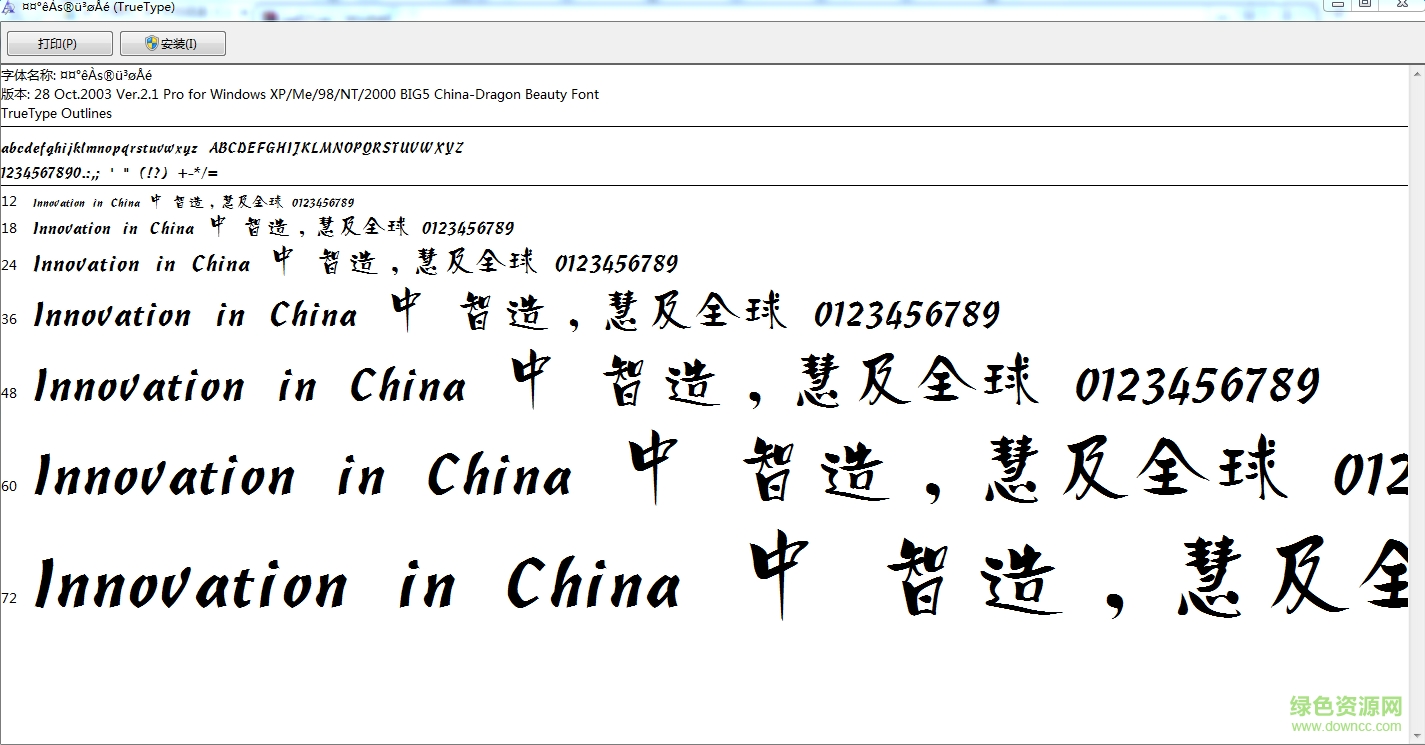
中國(guó)龍粗魏碑字體是一款中國(guó)風(fēng)字體軟件,字體粗獷狂野,給人一種整體彪悍的感覺,適合各種輕松場(chǎng)合,非常震撼,喜歡的朋友歡迎來(lái)綠色資源網(wǎng)下載體驗(yàn)!
在藝術(shù)設(shè)計(jì)和各種商業(yè)海報(bào)的制作中,字體的風(fēng)格選擇是十分重要的,不同的風(fēng)格字體都會(huì)造就不同的視覺效果。而中國(guó)龍粗魏碑字體是一套充滿中國(guó)風(fēng)的中文字庫(kù),綠色資源網(wǎng)給大家提供好看的中國(guó)龍粗魏碑字體!